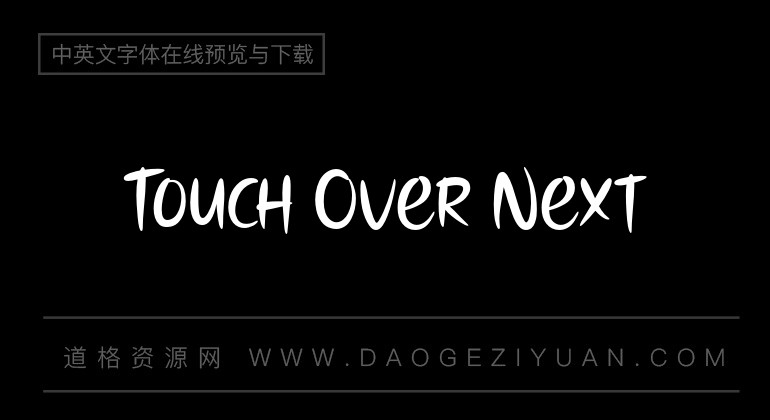
Touch Over Next
? Touch Over Next 字体是一款非常流行的日本字体,由森永乐印制所设计,该字体具有非常大的可读性,且具有平衡的行距,可以提升文本的可读性。Touch Over Next 字体具有粗体、斜体、拉丁文和日文等多种版本,可以满足不同类型的设计需求。此外,Touch Over Next 字体还可以在 Windows、Mac 和 Linux 系统上使用,是一款非常灵活的字体。
Touch Over Next是一款非常不错的手写艺术字体,具有很好的视觉感,适合于文化类的宣传设计、商业类品牌的广告和产品包装设计以及个性化文字排版等较多场景。